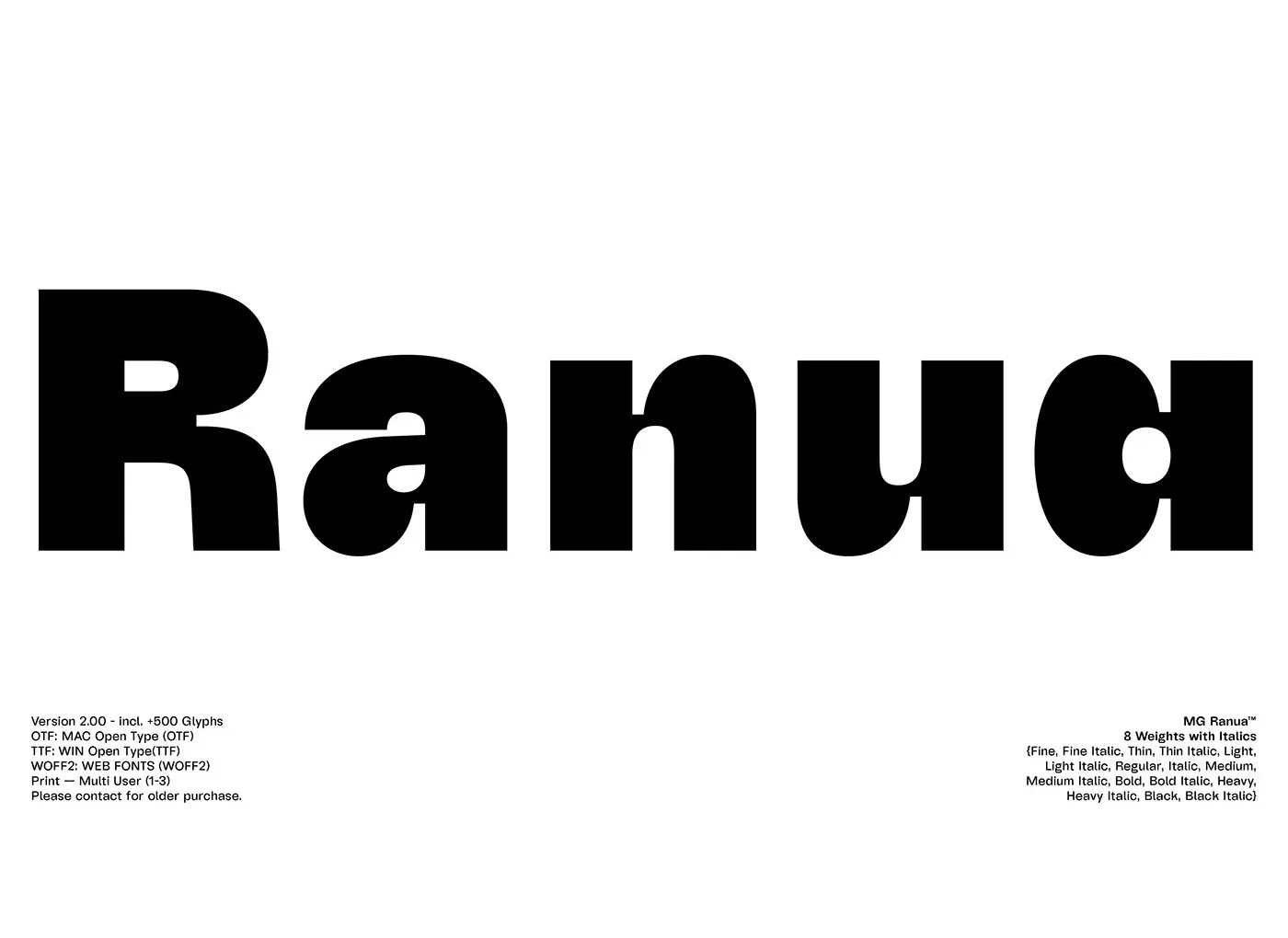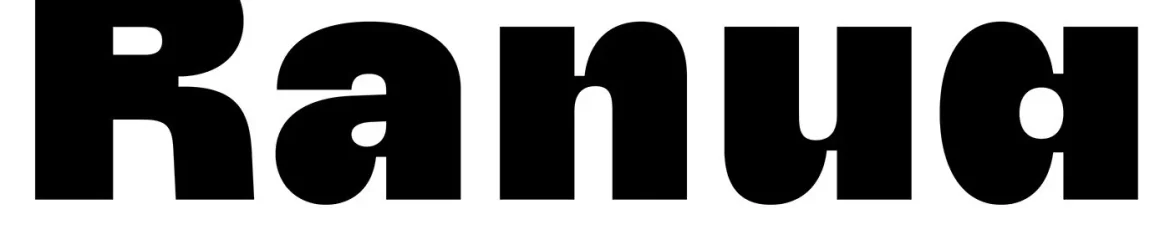
A fonte Ranua é uma família sans-serif projetada por Muhittin Güneş entre 2018 e 2019. Com sua propriedade de caixas de tinta profunda, ela oferece maior clareza para uso em grandes dimensões, como panos e ambientes maiores. Esta fonte foi projetada tanto para tela quanto para proporções maiores, adequada para um amplo range de aplicativos. Com 8 diferentes graus que incluem muito fino a grosso, cada grau da família Ranua contém cerca de 550 gráficos, cobrindo todo o alfabeto latino (A-Z), números e conjuntos alternativos de caracteres. Além disso, também oferece ligaturas padrão e não padrão, além de pontuação ordinal e frações. Seu design profundo em caixas de tinta ajuda a garantir que Ranua seja fácil de ler em grandes formatos, um fator essencial para aplicativos como panos publicitários ou grandes espaços comerciais. É uma escolha ideal tanto para designers digitais quanto para aqueles projetando material físico, pois garante legibilidade e profissionalismo sem comprometer a estética.